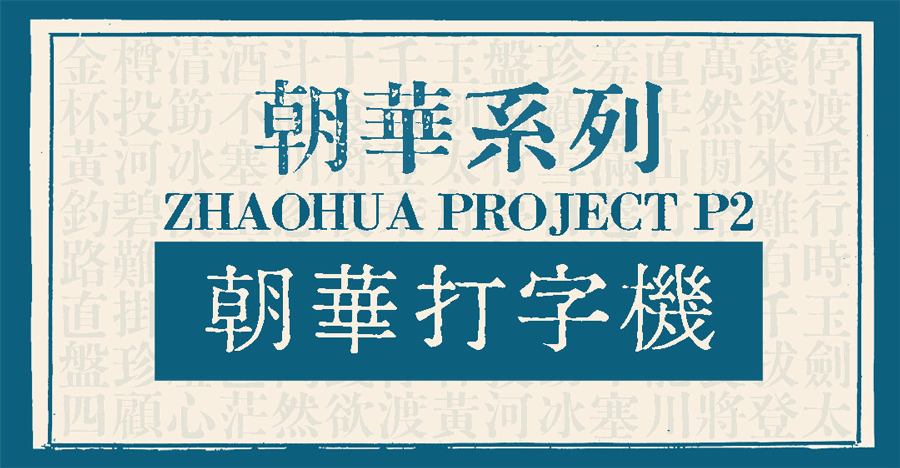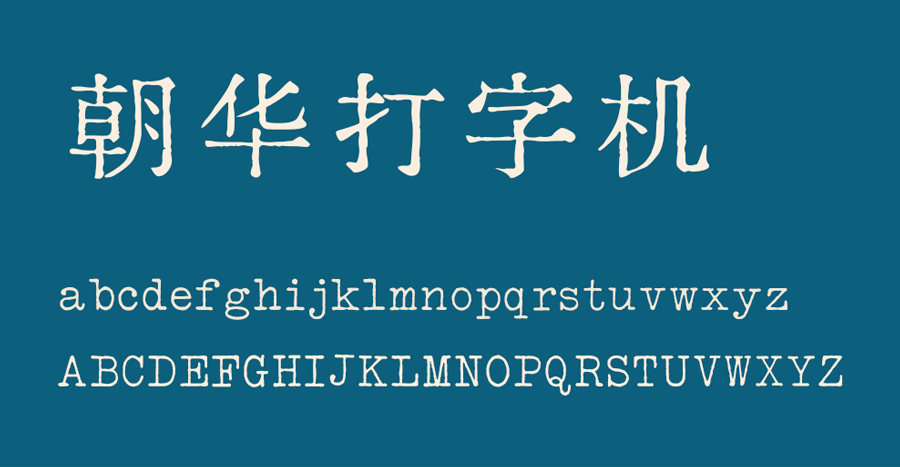
朝华打字机
朝华打字机(Zhaohua TypeWriter)是特里王制作的一款模仿打字机效果的免费可商用中文字体。作者以细明朝体为原型设计,完美还原了 20 世纪中文机械打字机(如上海双鸽牌)的铅字印刷质感。
字体笔画纤细,横竖对比清晰,线条简洁硬朗,没有现代字体的平滑圆润,而是略带机械感的拙朴,模拟出了油墨印在纸张上的复古效果,很适合用于复古设计、文创出版等领域。